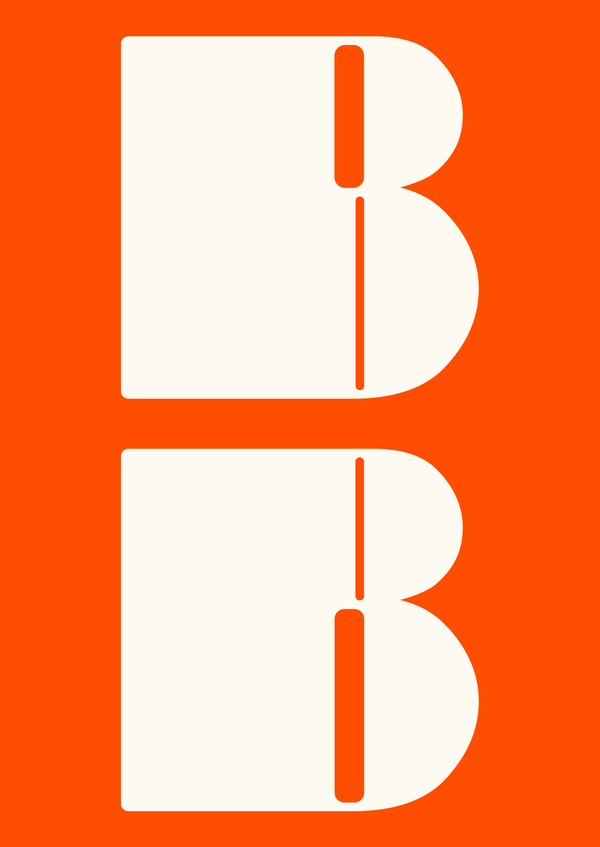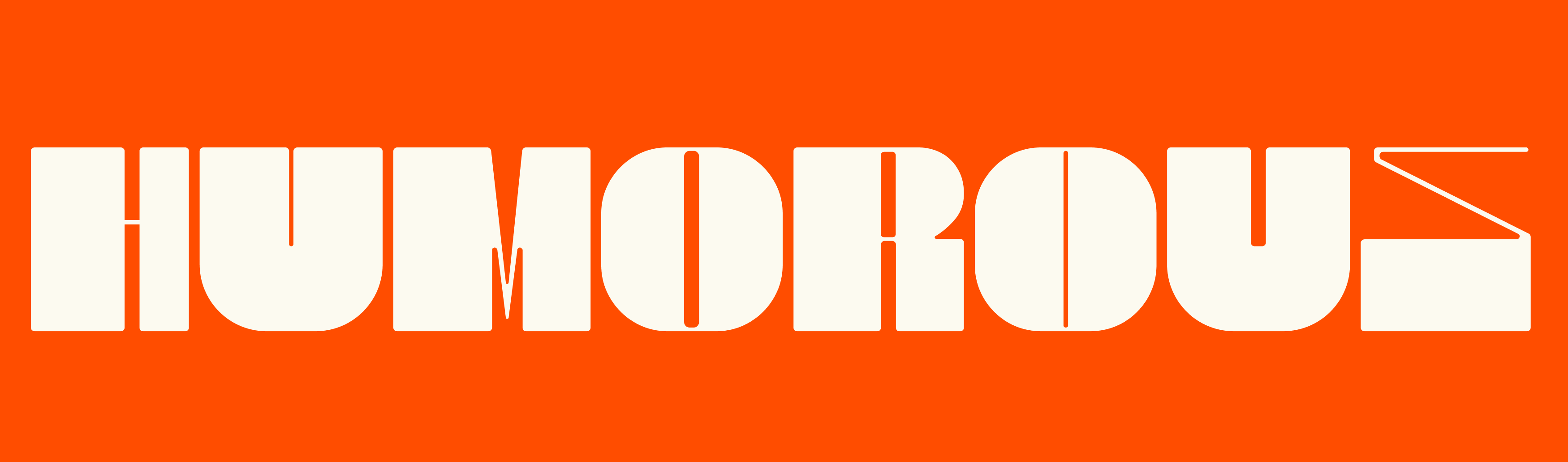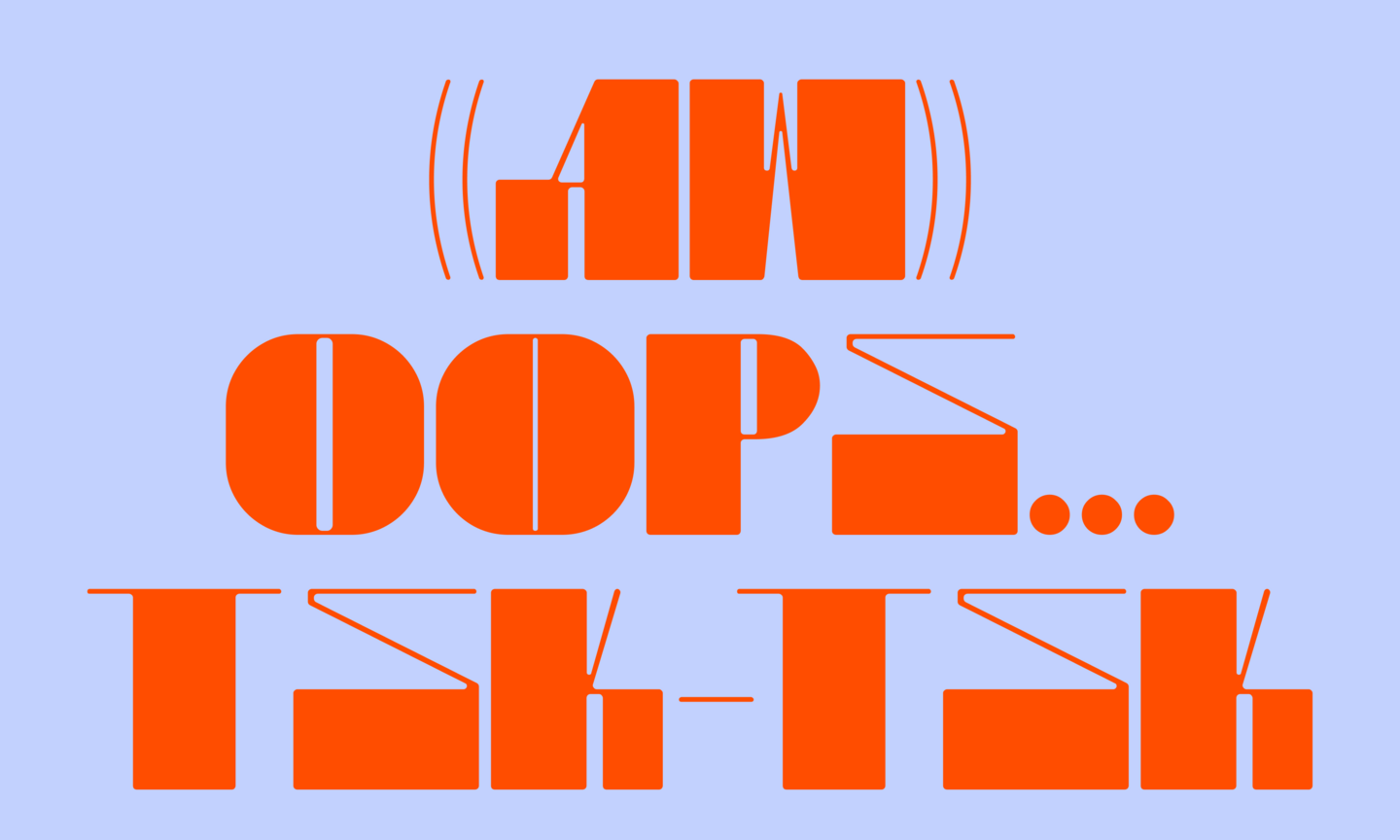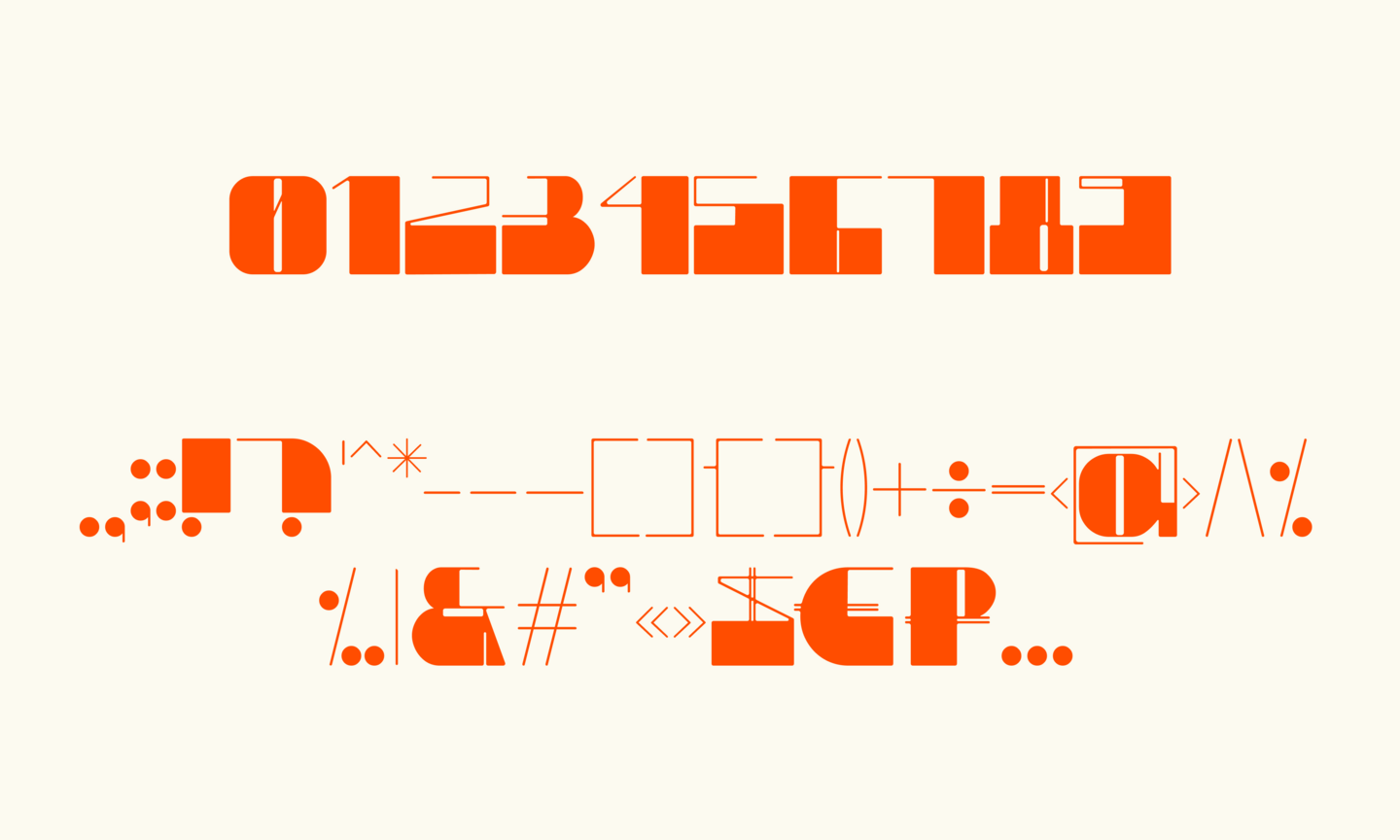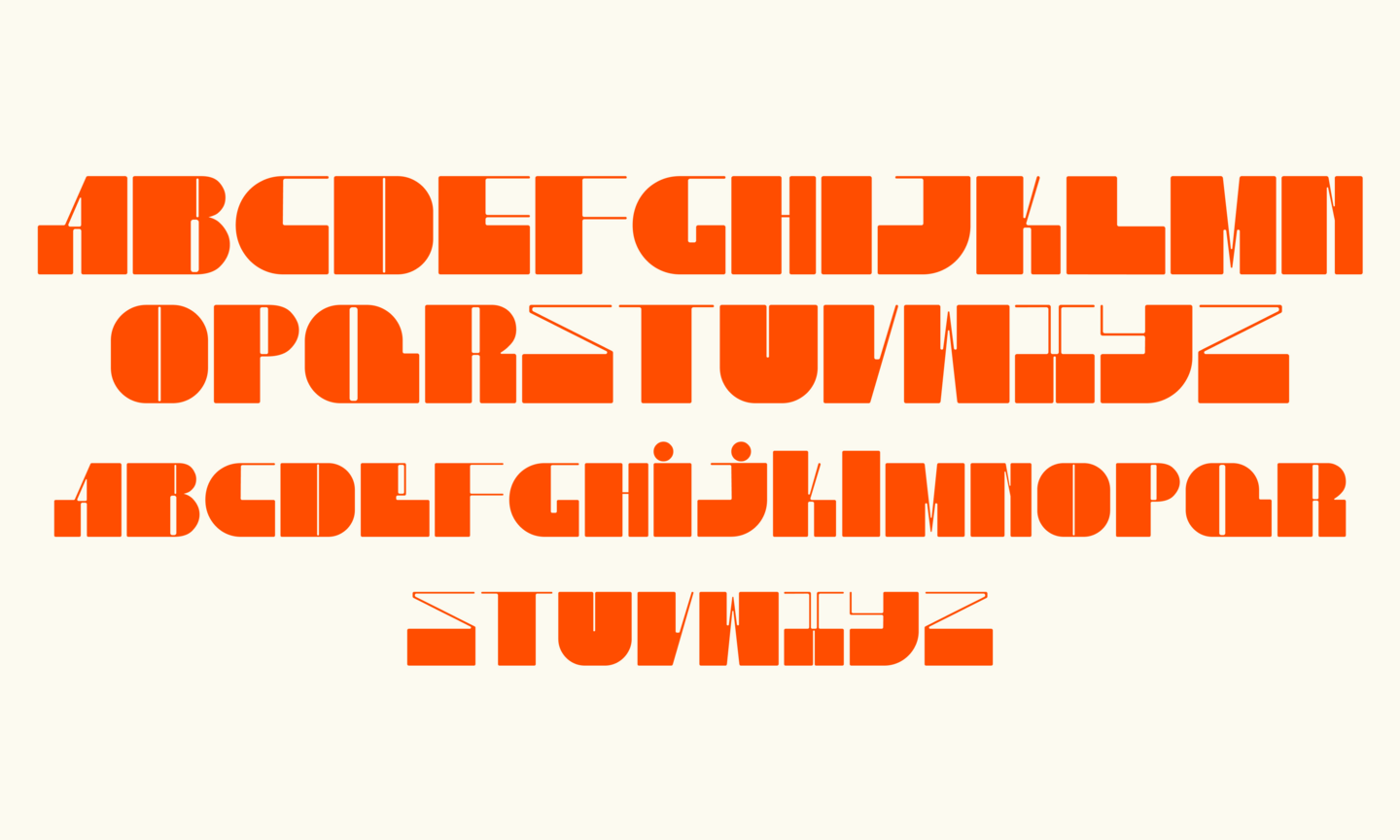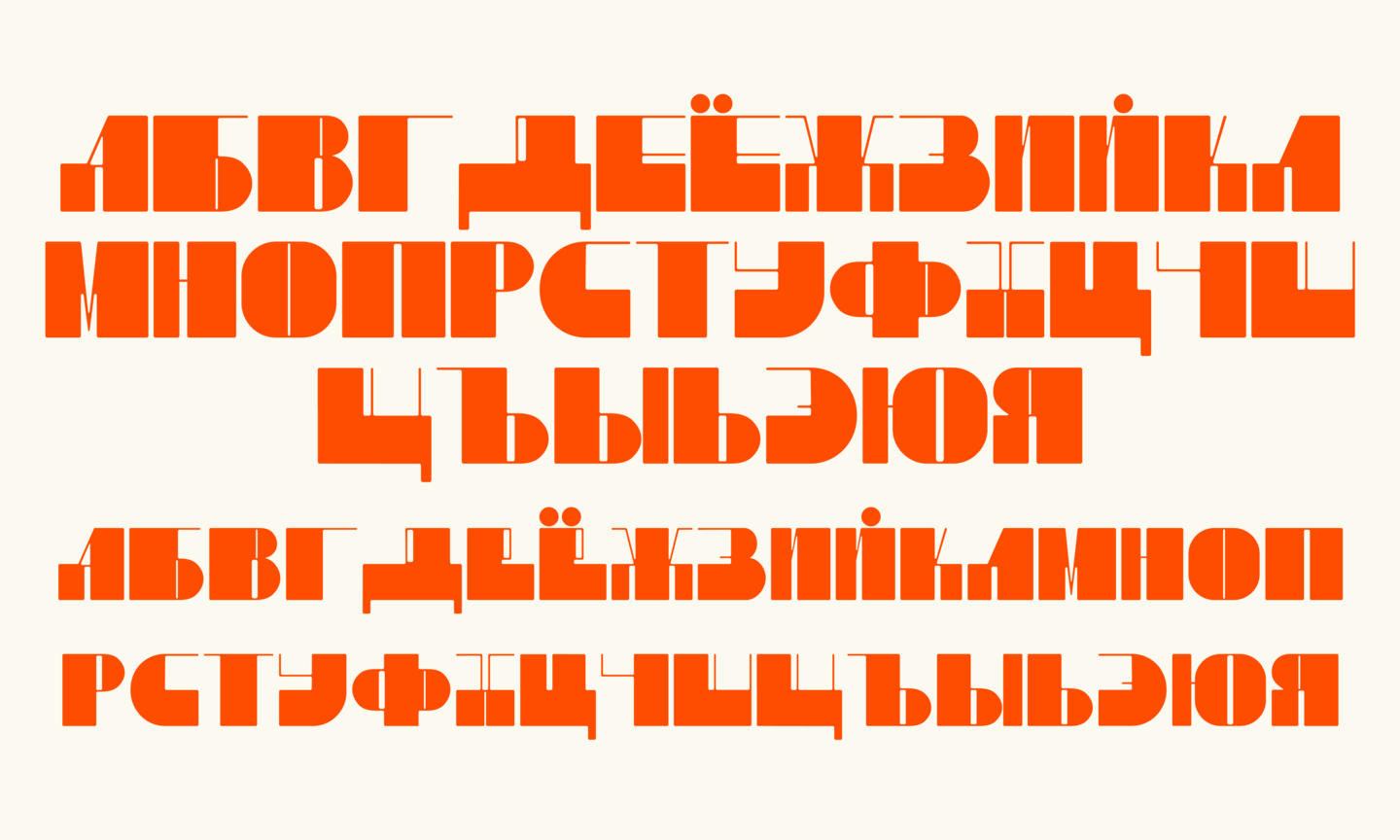
SHAPITO TYPEFACE
Shapito — акцидентный гротеск с игривым, немного дерзким характером. Основан на пластике уличного театра и передаёт его открытое, живое настроение.
Особенности шрифта — обратный контраст, вариативность внутрибуквенного пространства, плотный спейсинг.
Касса состоит из прописных и строчных знаков латиницы и кириллицы. Шрифт рекомендуется использовать для набора в крупном кегле.